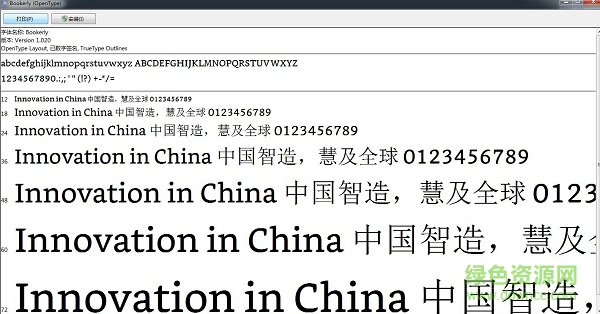
bookerly
bookerly字体是kindle电子书阅读器的专用衬线字体,清晰度高,可读性强,衬线特征明显,适合用于较长的文章阅读,用在排版方面非常棒,欢迎大家在本站免费下载!
bookerly字体介绍
Bookerly是亚马逊称其为专为数字屏幕阅读打造的新Kindle字体,这是一个定制的衬线字体,看上去比Caecilia字体更好,平板衬线Caecilia字体更适合标题文字,而不适合正文文字。